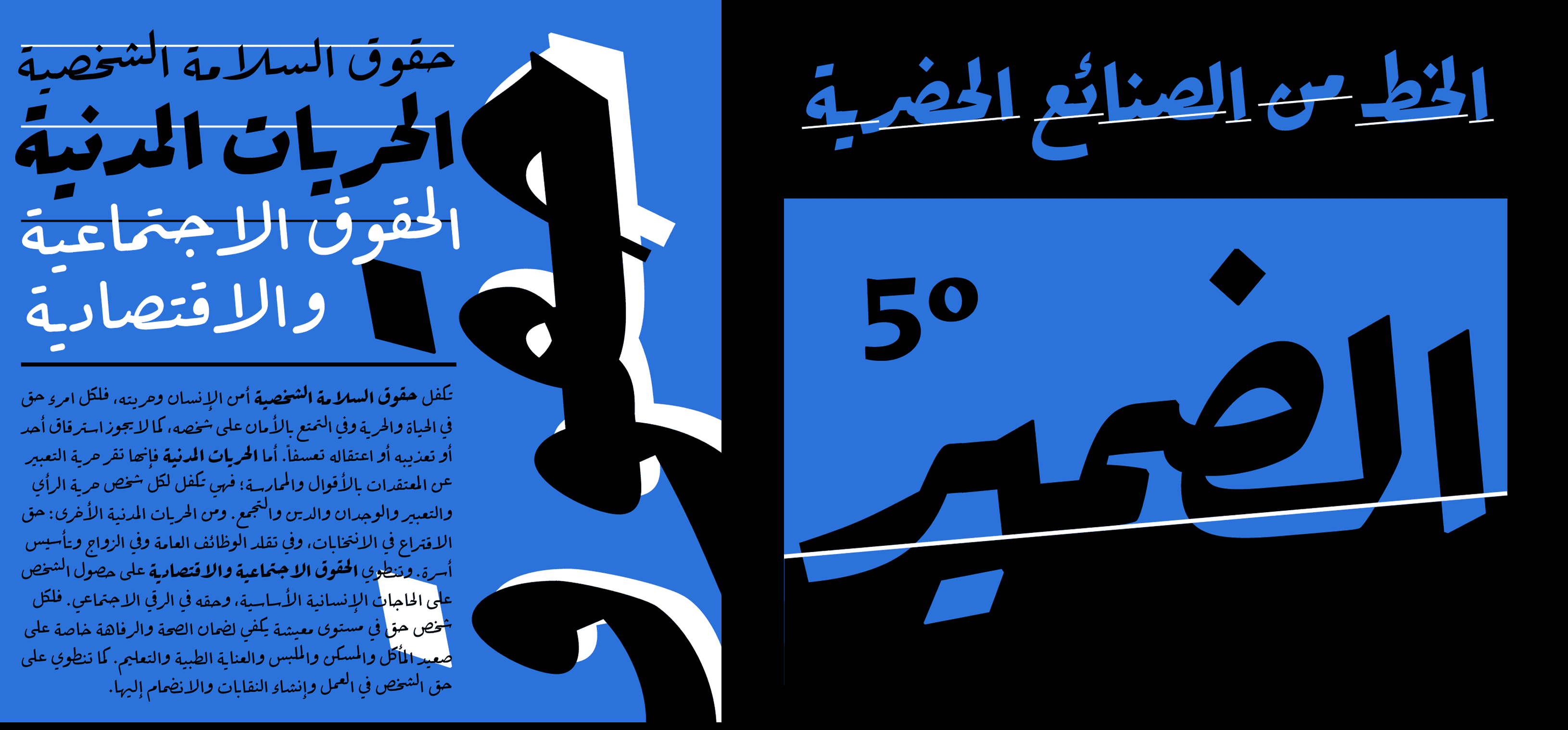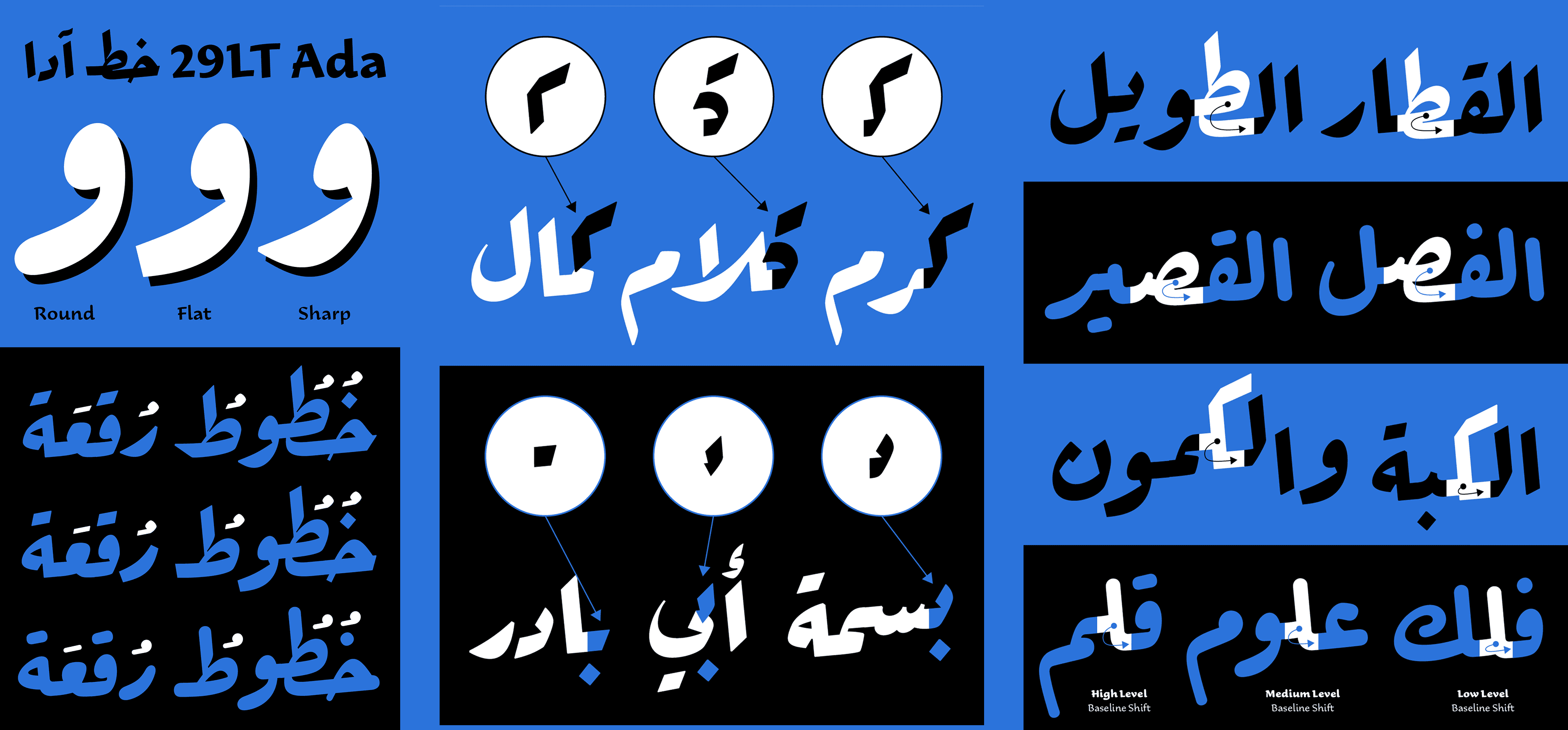
يستند خط آدا إلى أسلوب خط الرقعة الكلاسيكي، ويعيد تقديمه برؤية معاصرة من خلال ثلاثة أنماط مختلفة: الحاد (Sharp)، والمسطح (Flat)، والدائري (Round). يتميز الخط بثلاثة محاور تصميمية: الوزن، والتباين، والانحناء، مما يمنحه طيفًا واسعًا من التعبير الطباعي.